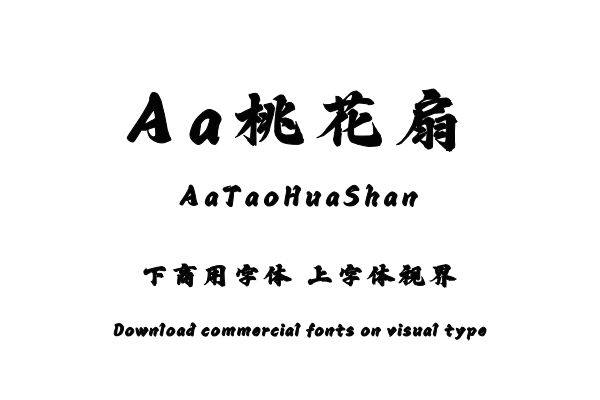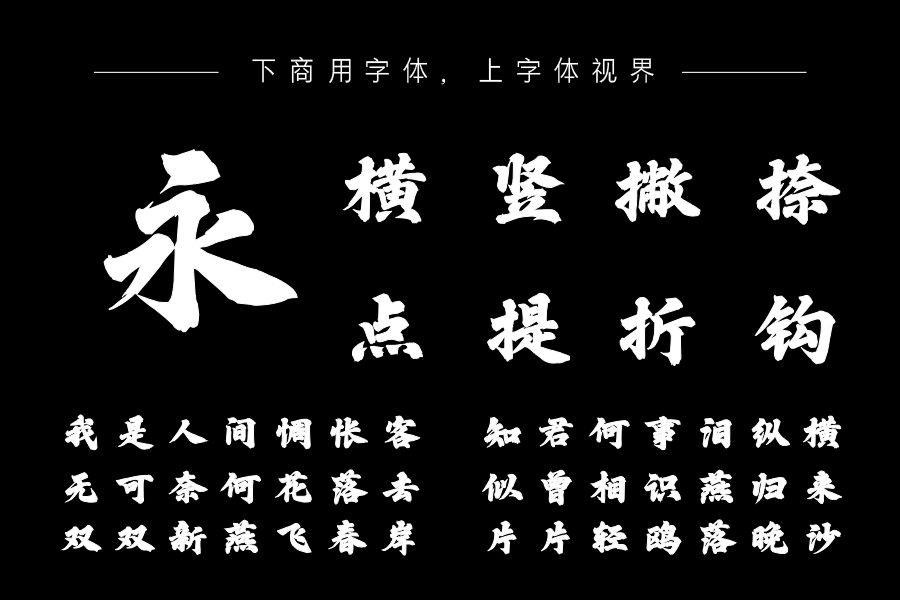
本字体用数码笔刷书写,纤细的连带与粗重的笔画形成对比,粗重醒目而富有耐看细节,细瘦有力的撇与宽大叶片状的捺也构成强烈反差,整字将传统楷书的粗细变化大大强化,构成......购买须知:“下载服务费”与“字体VIP”所获得字体 仅用于个人非商用, 商用请联系付费授权。本字体为电脑用字,手机没有root权限不支持直接手机换字(手机如何root,请自行百度搜索教程)。购买前请先 了解清楚后再付款 ,字体为虚拟产品无法回收 一旦购买不支持退款。